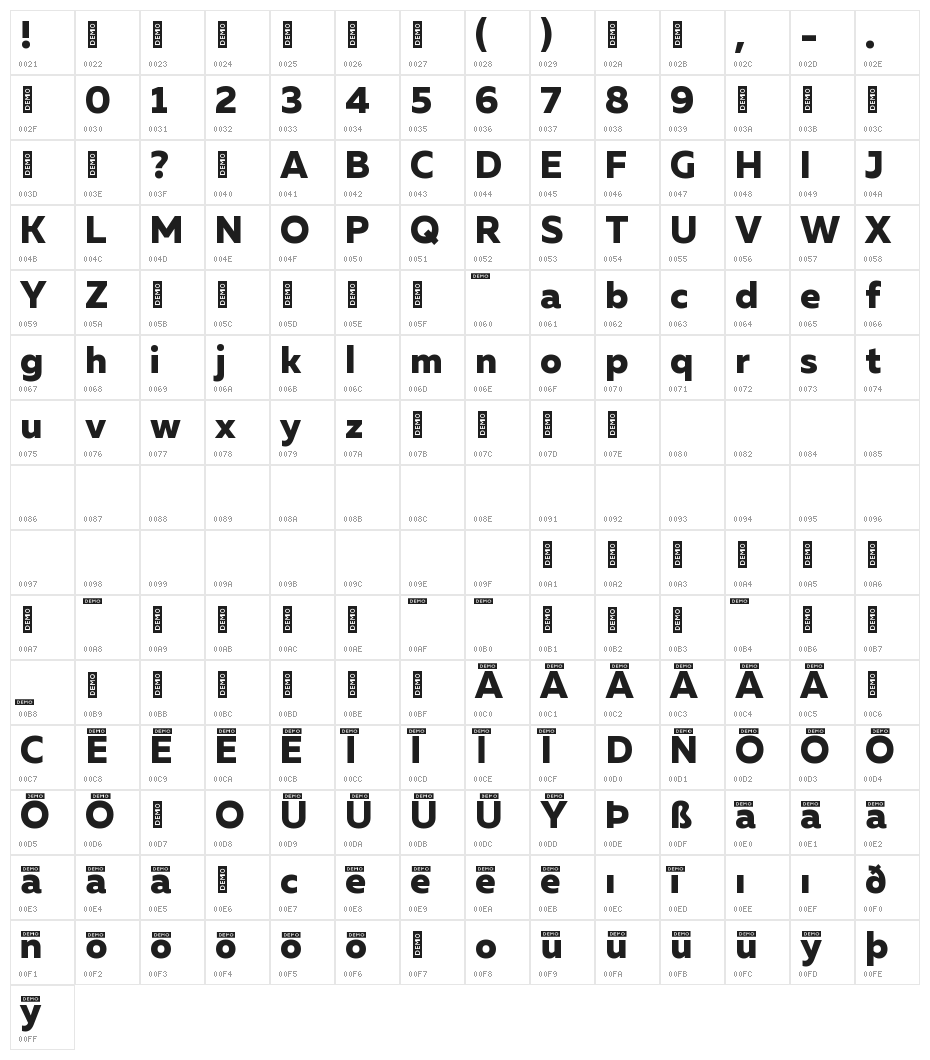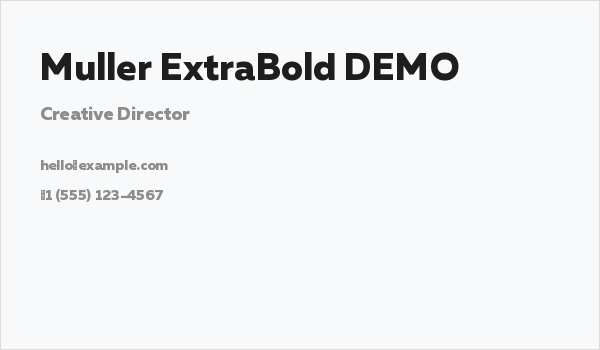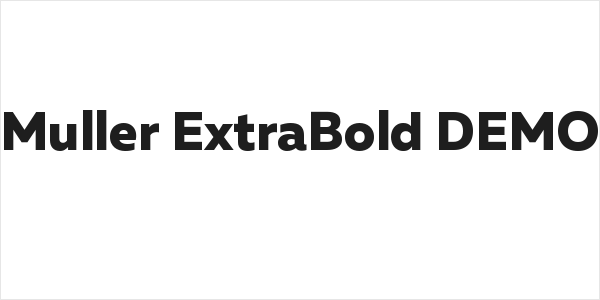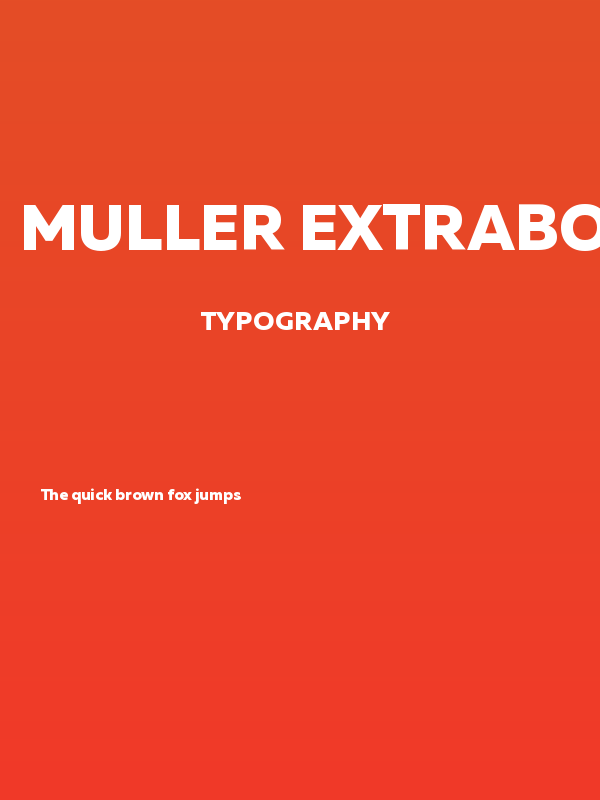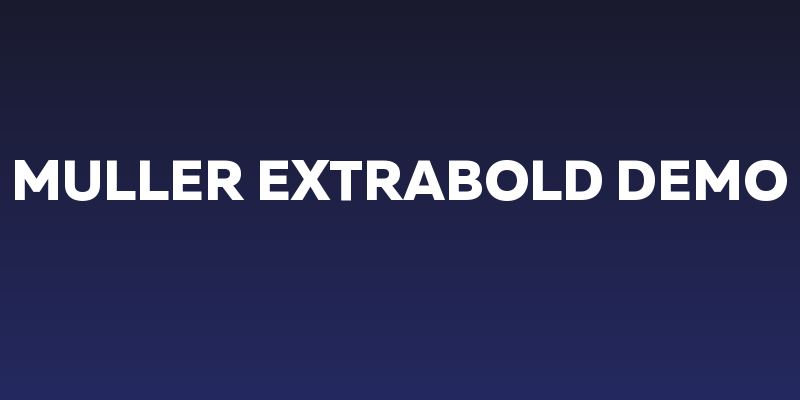
Muller ExtraBold DEMO Font
✎ Sans Serif
| Anwendungsfall | Headlines, Logos, Branding |
| Vorgeschlagene Projekte | Ideal for branding, headlines, posters, and digital media where a strong, modern look is desired. |